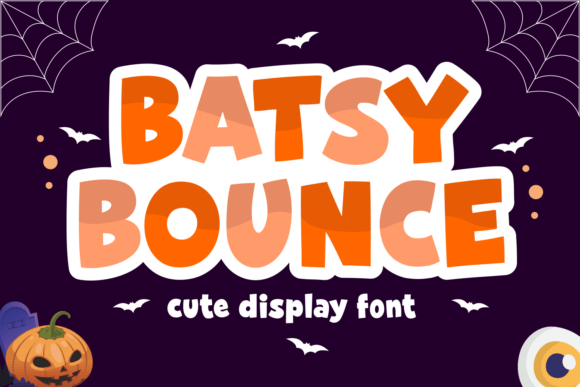
Batsy Bounce Font by Dreamink 7ntypes
Att hitta rätt designelement kan vara utmanande, men Batsy Bounce Font by Dreamink 7ntypes erbjuder en exceptionell samling som omedelbart lyfter ditt arbete.
Oavsett om du skapar POD-produkter (Print on Demand), bröllopsinbjudningar eller grafik för sociala medier, är Batsy Bounce Font by Dreamink 7ntypes ett perfekt val.